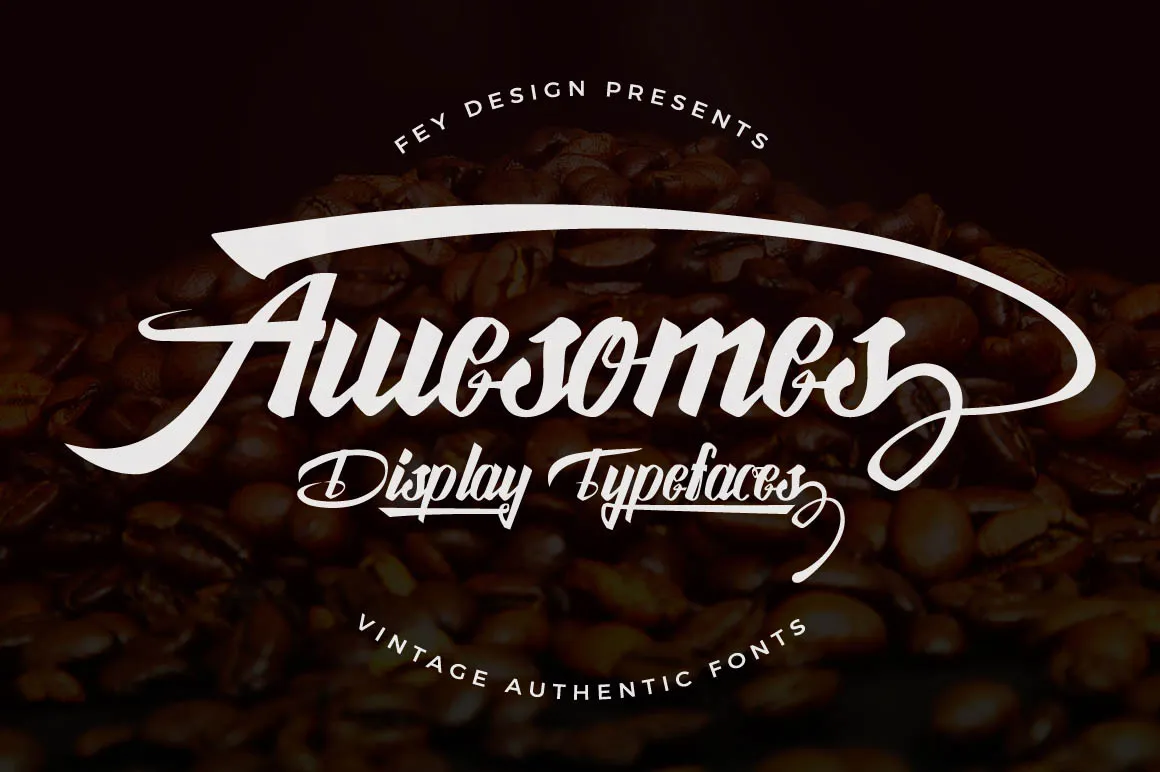
Esta fonte de alfeite única foi desenvolvida pela Feydesign, e seu estilo elegante e moderno torna-a uma escolha perfeita para projetos criativos novos. A designer Hamilton não apenas reforça essa qualidade, mas também adiciona um toque especial ao design do alfeite. Perfeita tanto para uso em cartões de aniversário quanto para criações digitais, esta fonte é uma opção ideal se você está procurando algo novo e atraente para seus próximos projetos gráficos. Com o seu charme chamativo e sofisticado, a ‘Awesome Font’ em alfeite certamente será um dos principais destaques de qualquer projeto visual.